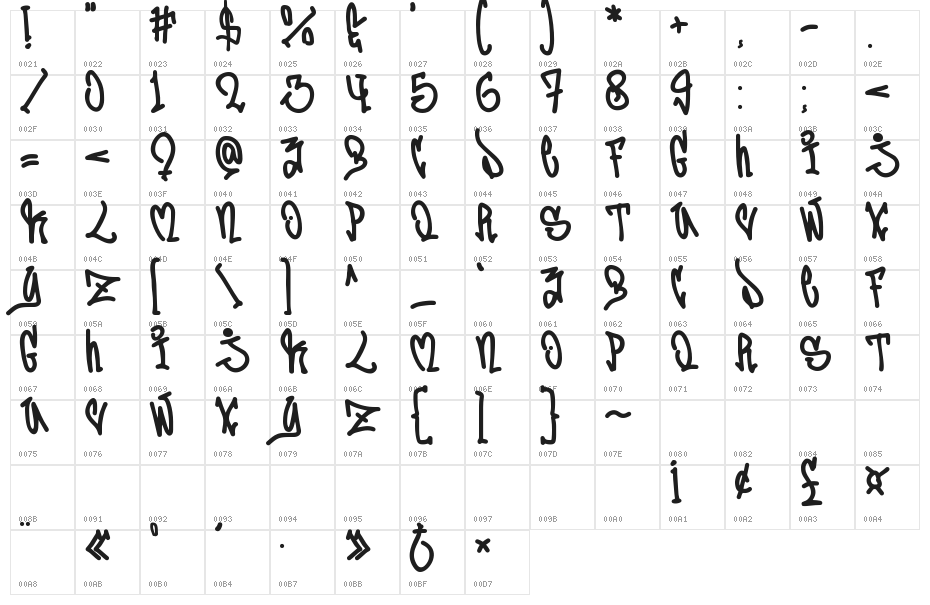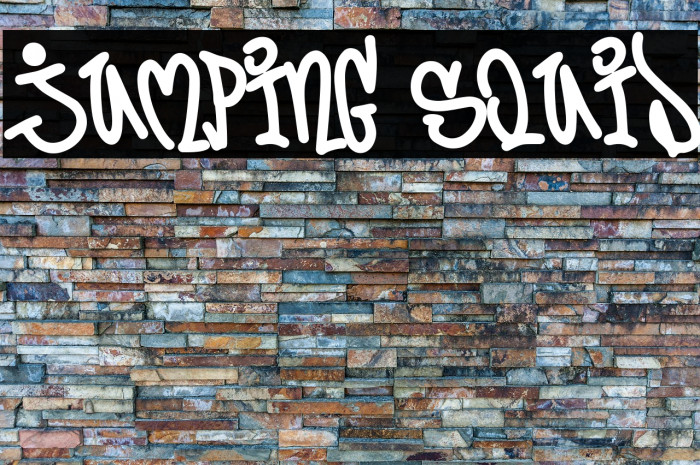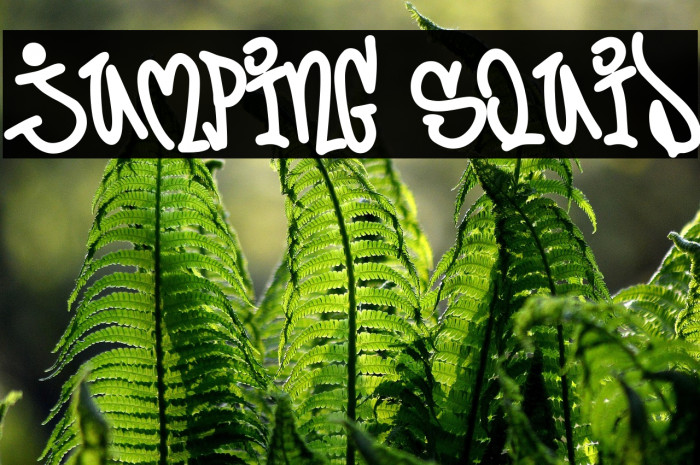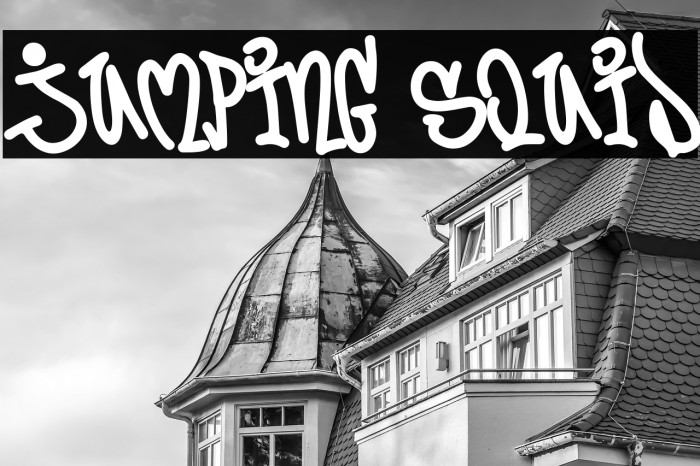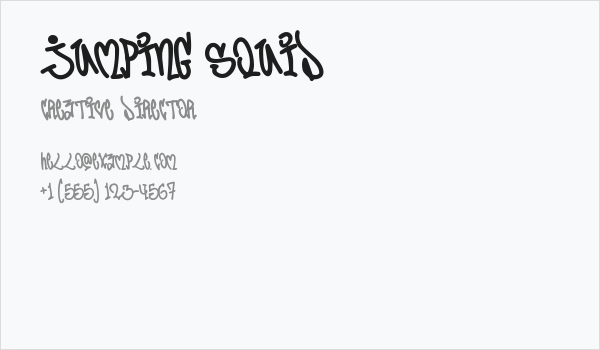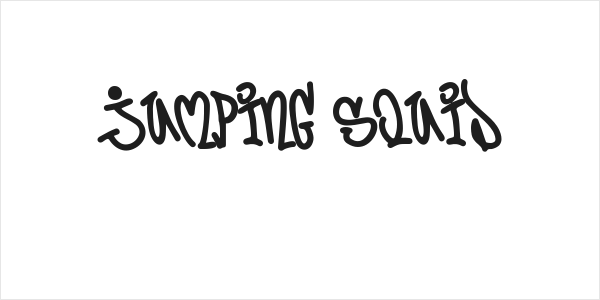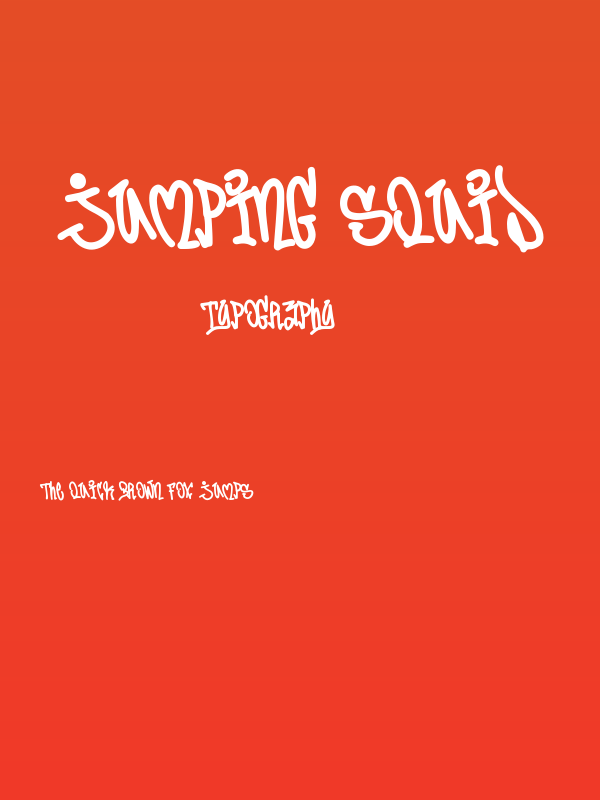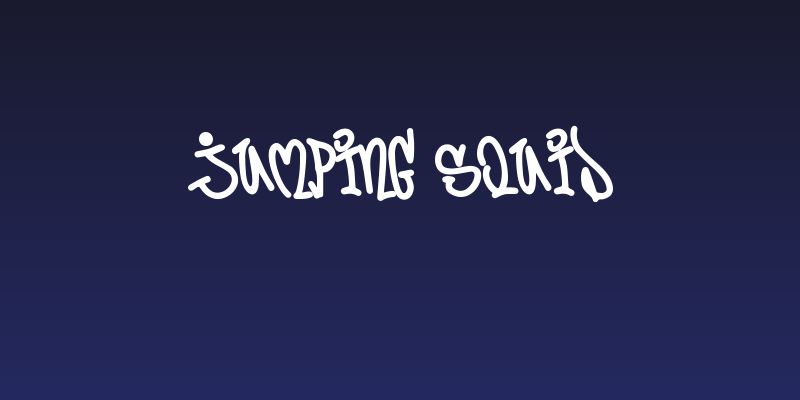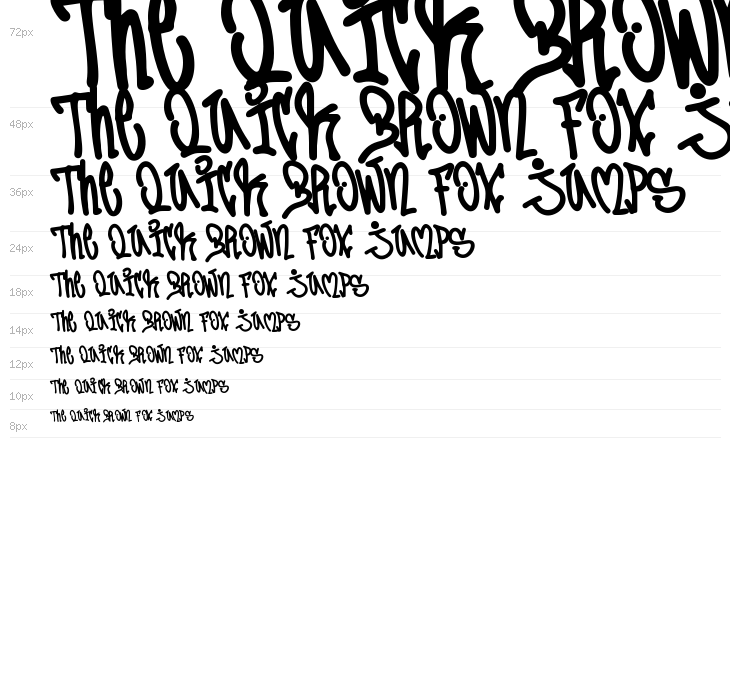
Jumping Squid Font
| Kategorien | Graffiti |
| Gesamtstil | Modern, Urban |
| Vorgeschlagene Projekte | Ideal for street art designs, urban-themed posters, music album covers, and creative branding projects. |